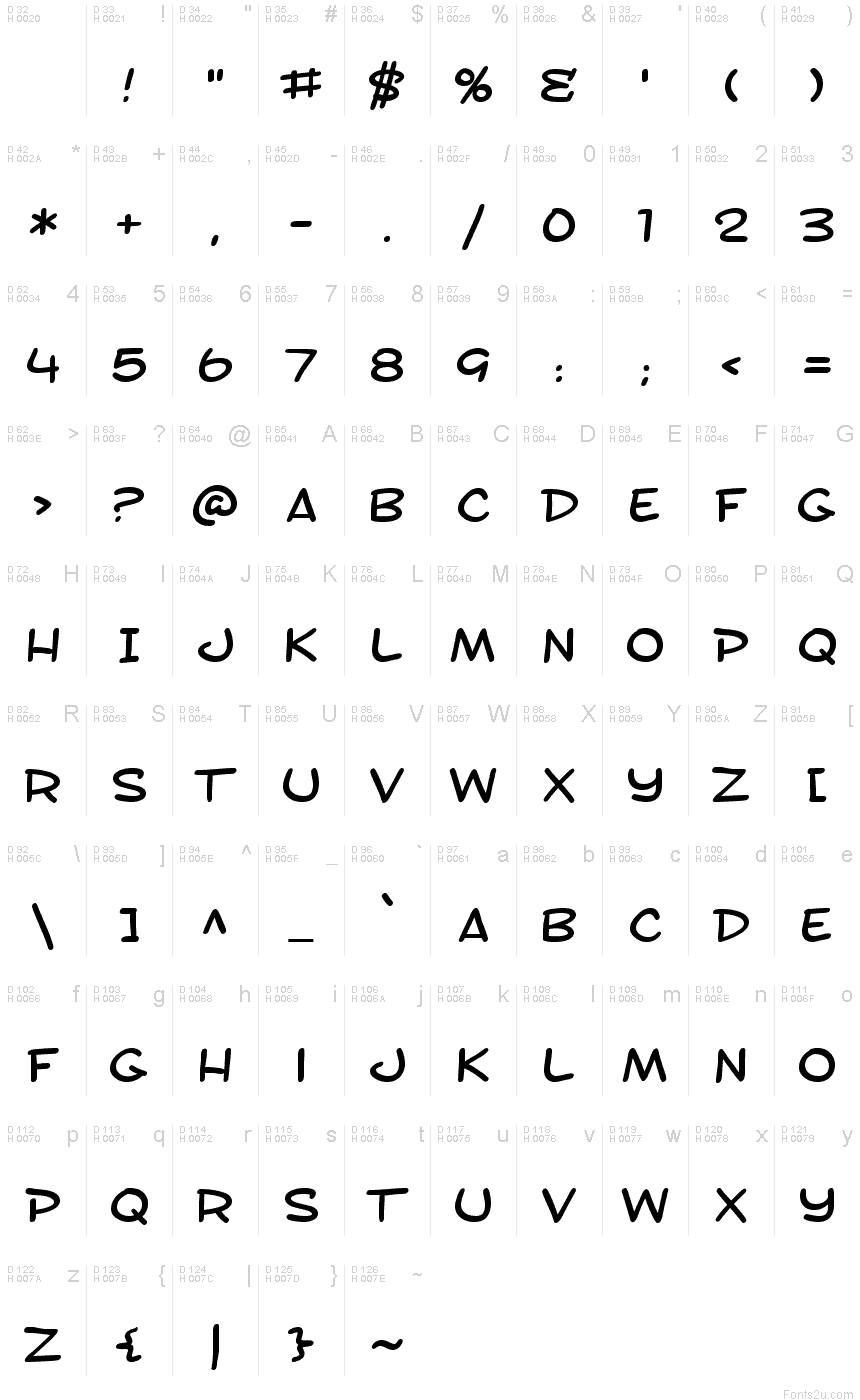
SF Toontime Extended
SF Toontime Extended od ShyFoundry to darmowy, odręczny krój pisma w stylu cartoon, utrzymany w wielkich literach, który oddaje luźny charakter i grubą kreskę klasycznego komiksowego liternictwa. Litery są szerokie, miękkie i lekko nieregularne, a zaokrąglone kształty oraz naturalne odstępy sprawiają, że cały alfabet jest zabawny i daleki od sztywnej elegancji.
Idealnie pasuje na okładki książek dla dzieci, tytuły komiksów, zaproszenia na imprezy, opakowania przekąsek czy radosne nagłówki plakatów, gdzie darmowy font z tak dużą dawką energii potrafi przyciągnąć wzrok samą swoją osobowością. Szerokie, otwarte kształty świetnie sprawdzają się również w monogramach, inicjałach i krótkich logotypach, które mają emanować przyjaznym klimatem poranków z kreskówkami.
ShyFoundry
Derek Vogelpohl